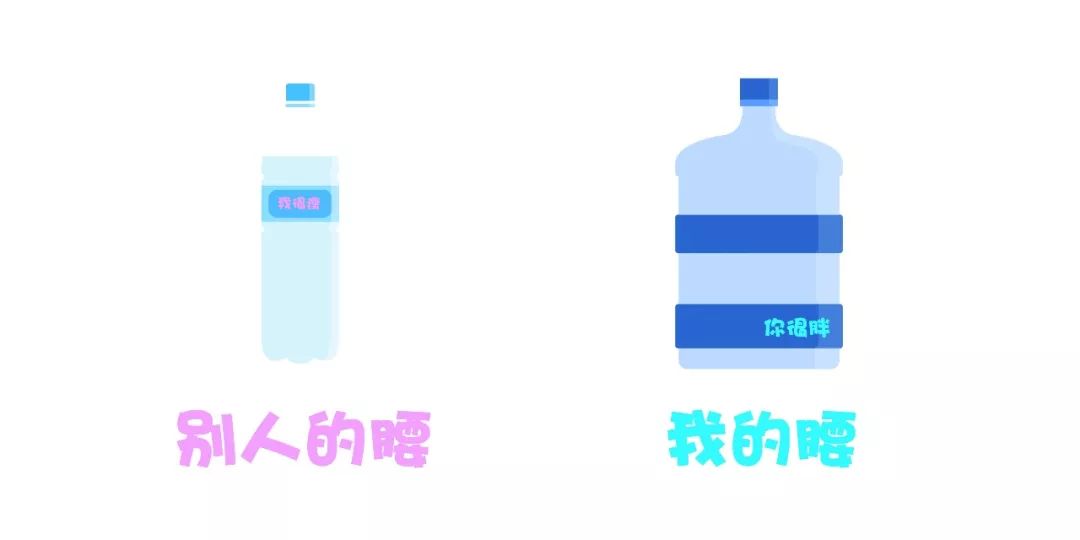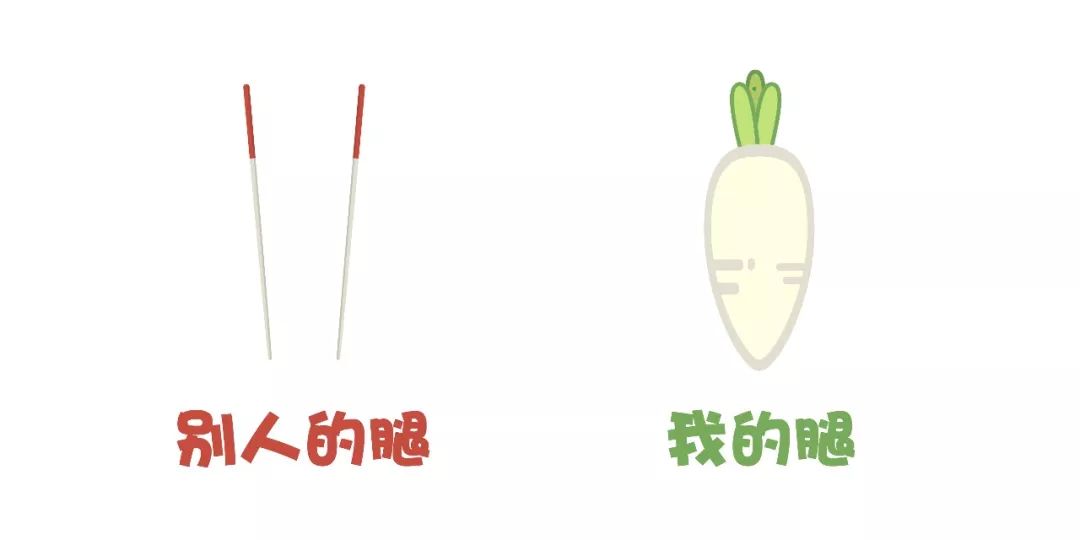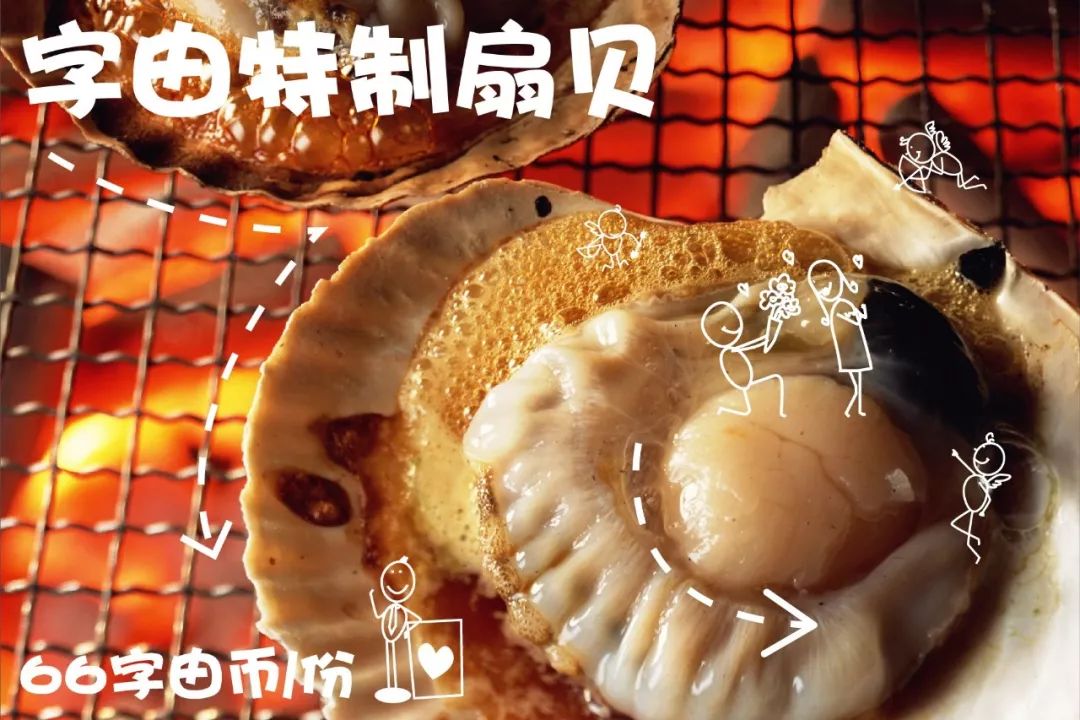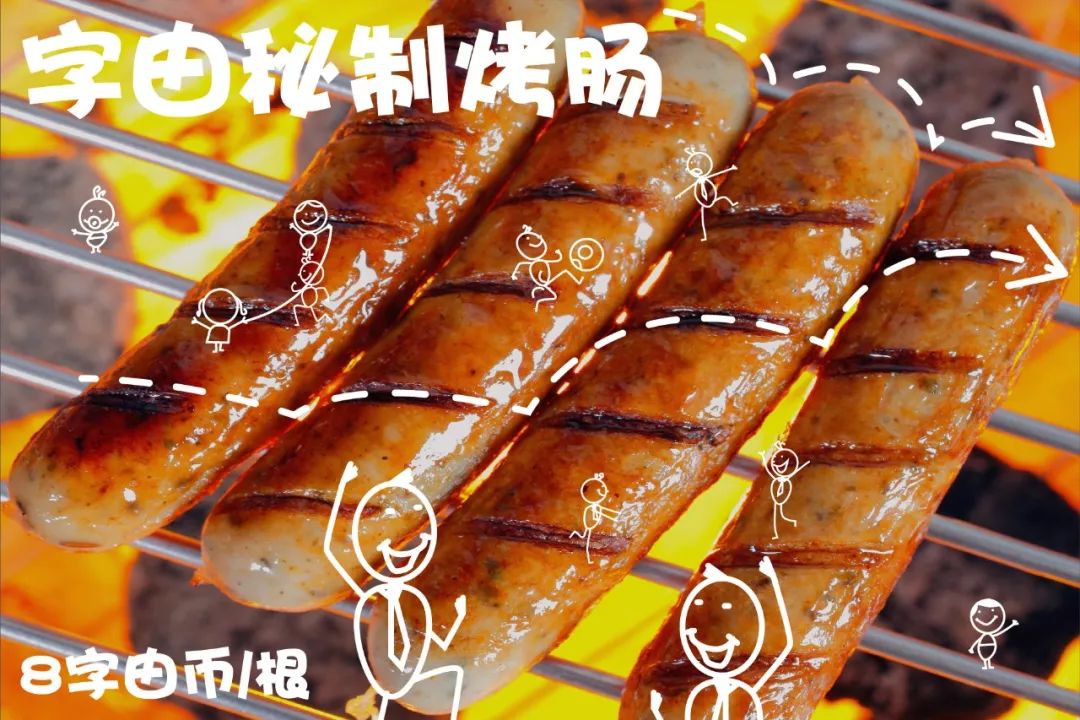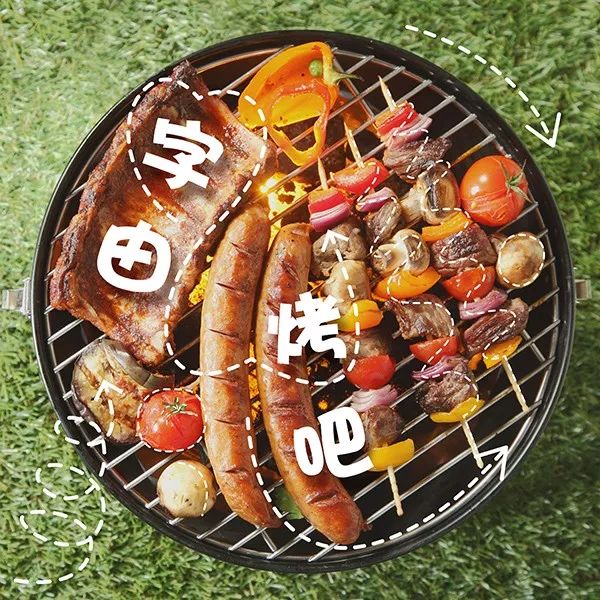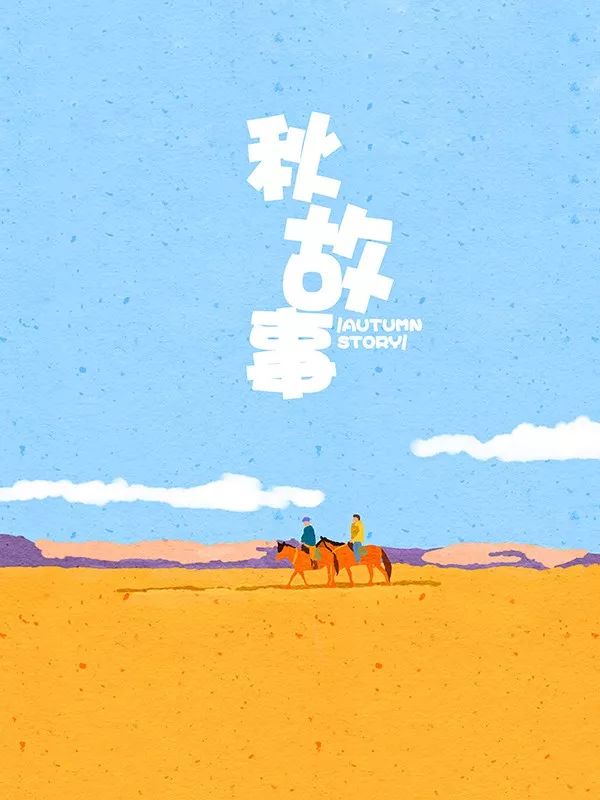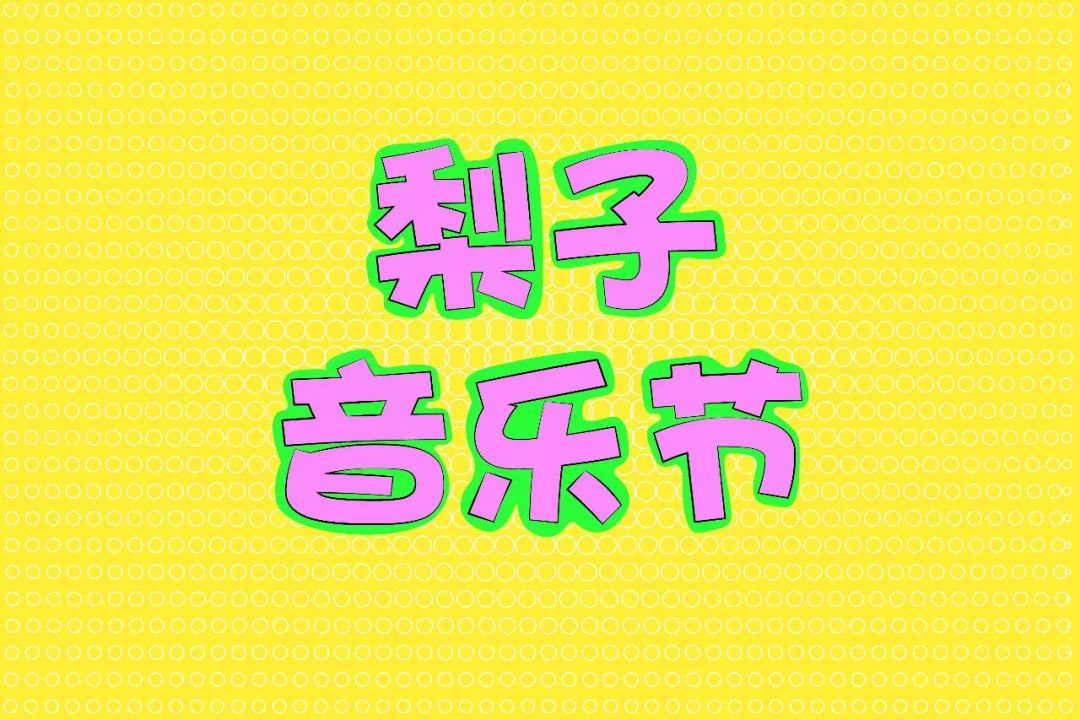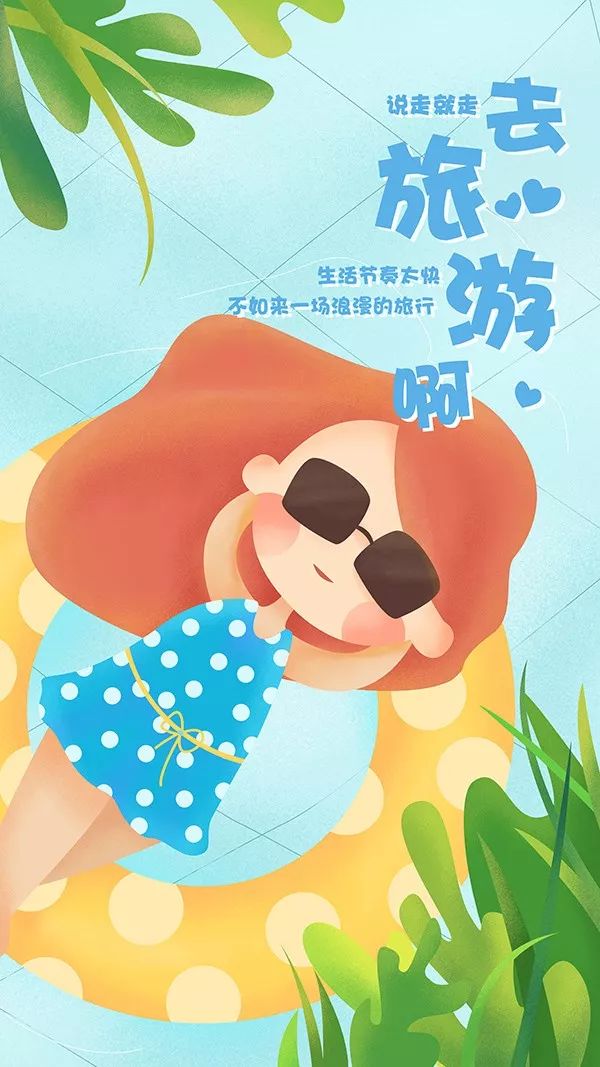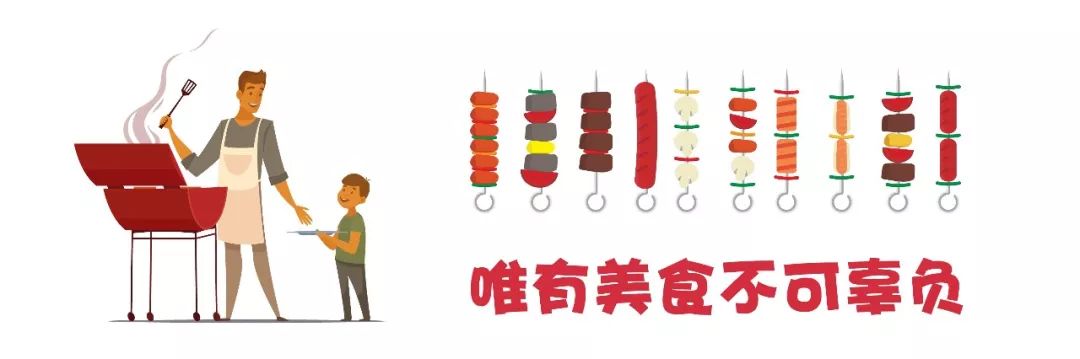
华康海报体字体介绍,华康海报体设计灵感和使用案例
就像没有 华康海报体 的菜单,
食物看起来是乏味的。
短短几字搭配海报体,
瞬间食欲大增,
让人一口气吃五串不费劲!!
什么体重,什么赘肉,
等我撸爽了再说!
而这些也只展现了海报体的部分魅力
它还可以这样
也可以这样
这样对它来说也是小case
如此优质的字体还不赶快去试试